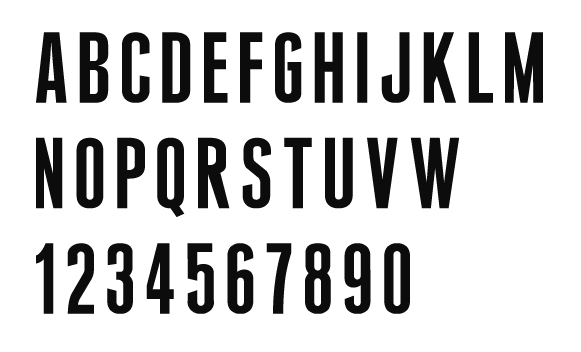
Welcher schmale Headline-Font ist das!
Hat jemand eine Idee welche Schrift das sein könnte? Ich hab zwar einige ähnliche Schriften gefunden aber die sind eben nur ähnlich ...
Eine Freundin sucht die Schrift und hat bisher nur diesen schlechten FreeFont-Clone gefunden.
Mich erinnert die Schrift an die Venus. Die hat so einen schmalen Schnitt aber nicht. Die Monotype Grotesque ist es auch nicht, deren schmale Ausgabe sieht ganz anders aus. :?
Eine Freundin sucht die Schrift und hat bisher nur diesen schlechten FreeFont-Clone gefunden.
Wo gibt's den denn?
Das könnte eine "verfeinerte :cry: " Heroic Condensed Bold sein:
Sieht aus wie eine alte Holzbuchstabenschrift. Ich habe mit sowas in den 70ern noch Plakate gesetzt: Schützenfest, Fussballturnier u.s.w.
Damals habe ich mich schon gefragt: Mensch, wer macht eigentlich solch' seltsame Schriften?
Hier sind zwar keine Schrägen drin, kommt dem aber recht nahe:
Die Schrägen kannst du ja auch selber hinzufügen :hammer:
Hab sie gefunden: Die Schrift stammt von Eriq Jaffe und ist ein Nachbau der Schrift, die die Baseball-Mannschaft »Houston Astros« auf ihren Trikots benützt. Vielleicht kann jemand herausfinden, welche Schrift das ist?
ich suche diese schrift und in der tat, der clone-font nennt sich MLB astros.
dann gibts den wohl nur in dieser nachbau-variante, schade. weil nach astros hab ich schon geforscht und bin auch nur bei den houstons gelandet.
die heroic kommt der sehr nahe, aber in der tat bin ich an den schrägen interessiert. mal sehen, was sich machen läßt.
… die heroic kommt der sehr nahe, aber in der tat bin ich an den schrägen interessiert …